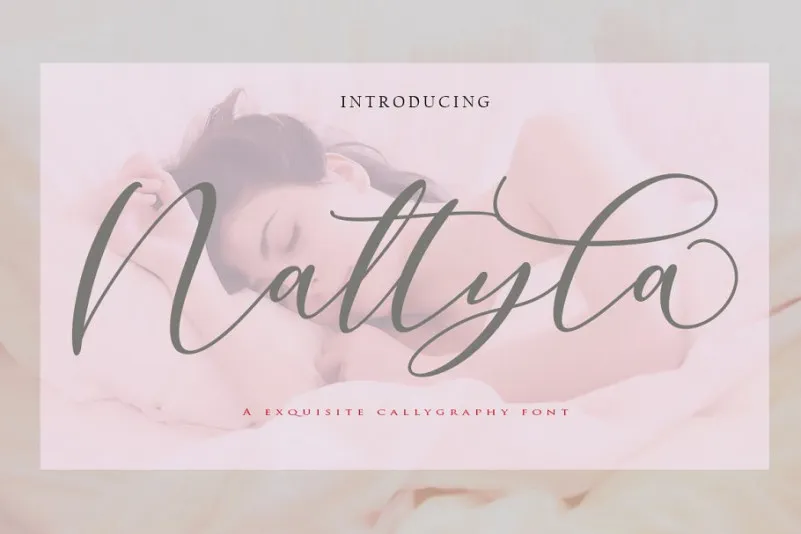
Nattyla Calligraphy Font – Fonte Grátis
Nattyla Calligraphy Font
Bem-vindo à Nattyla Calligraphy Font! Esta nova tipografia moderna traz a elegância da calligrafia escrita manualmente. Introduzida pelo designer C00zona, esta fonte se destaca por sua própria fluidez e personalidade sofisticada. Perfeita para branding, convites de casamento, revistas, têiseres, cartões de negócio, citações, posters e muito mais, a Nattyla Calligraphy Font é uma excelente escolha para quem busca um estilo único na sua próxima criação visual. Se você quiser experimentar antes de comprar, não há melhor maneira do que começar com esta fonte moderna que reflete o estilo da escrita atual.